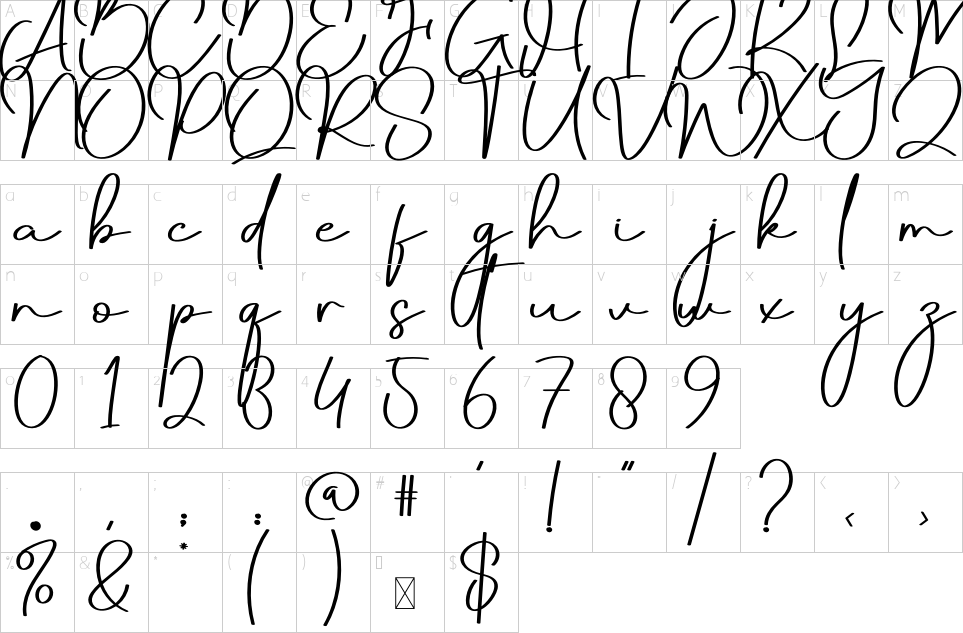
Aqui está uma descrição para a página de download da fonte ‘Monday Font | 1001 Free Fonts’, mantendo o tom informativo e convidativo, sem criar características fictícias: Descubra a simplicidade e a clareza de Monday Font, uma elegante e confortável fonte gráfica que se destaca na categoria de fontes gratuitas. Desenvolvida por scratchones, esta font é perfeita para estilos contemporâneos e modernos. Suavizada e versátil, Monday é adequada para textos de newsletter, design de logotipos ou até mesmo aplicativos de celular. Com um design simples e limpo, Monday é uma ótima escolha para qualquer projeto de design. Baixe a sua hoje e veja por si mesmo como ela se destaca entre as diversas fontes disponíveis.